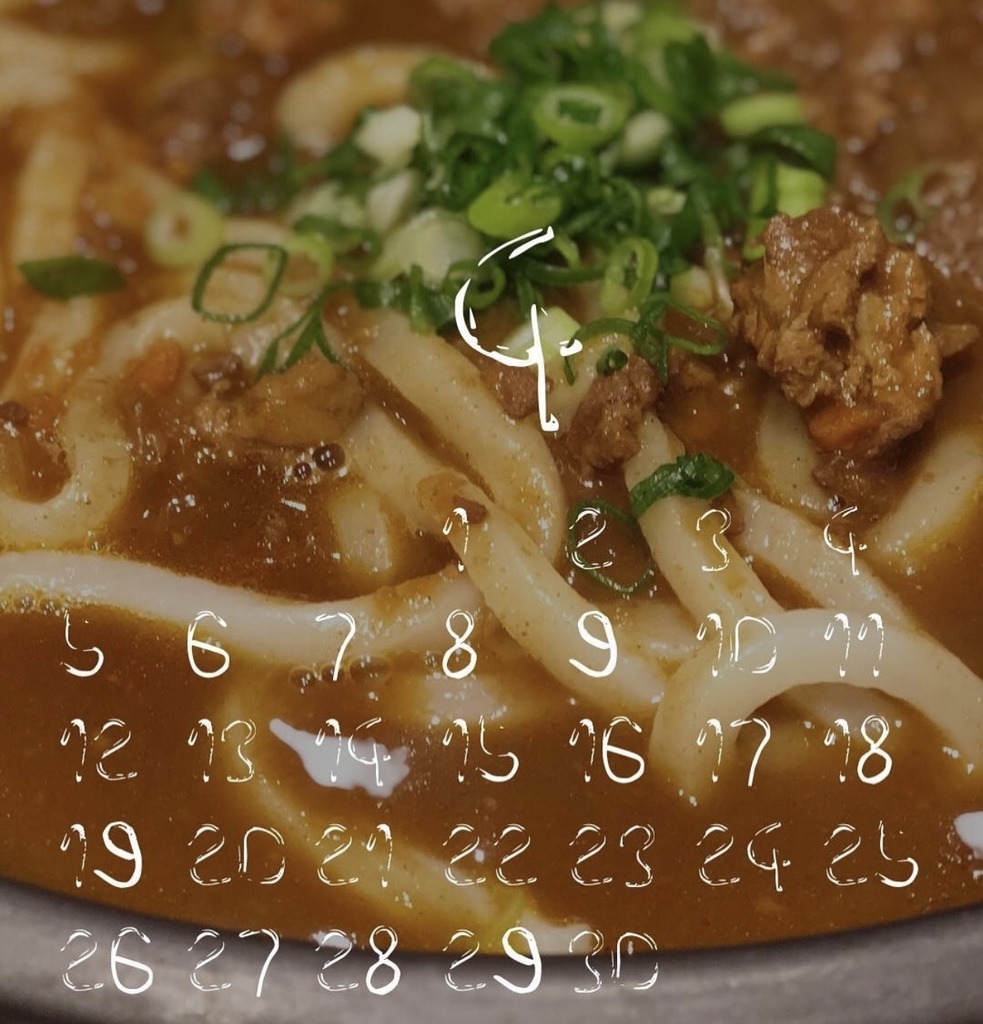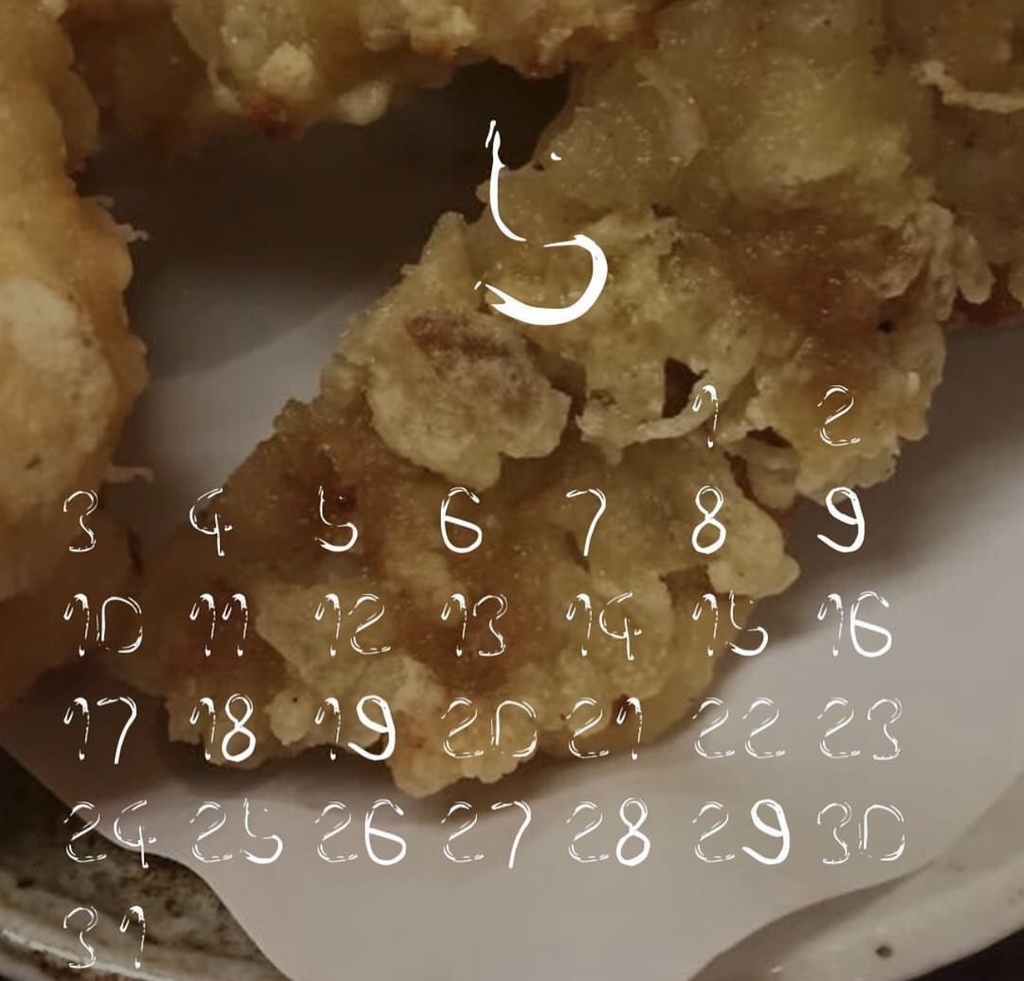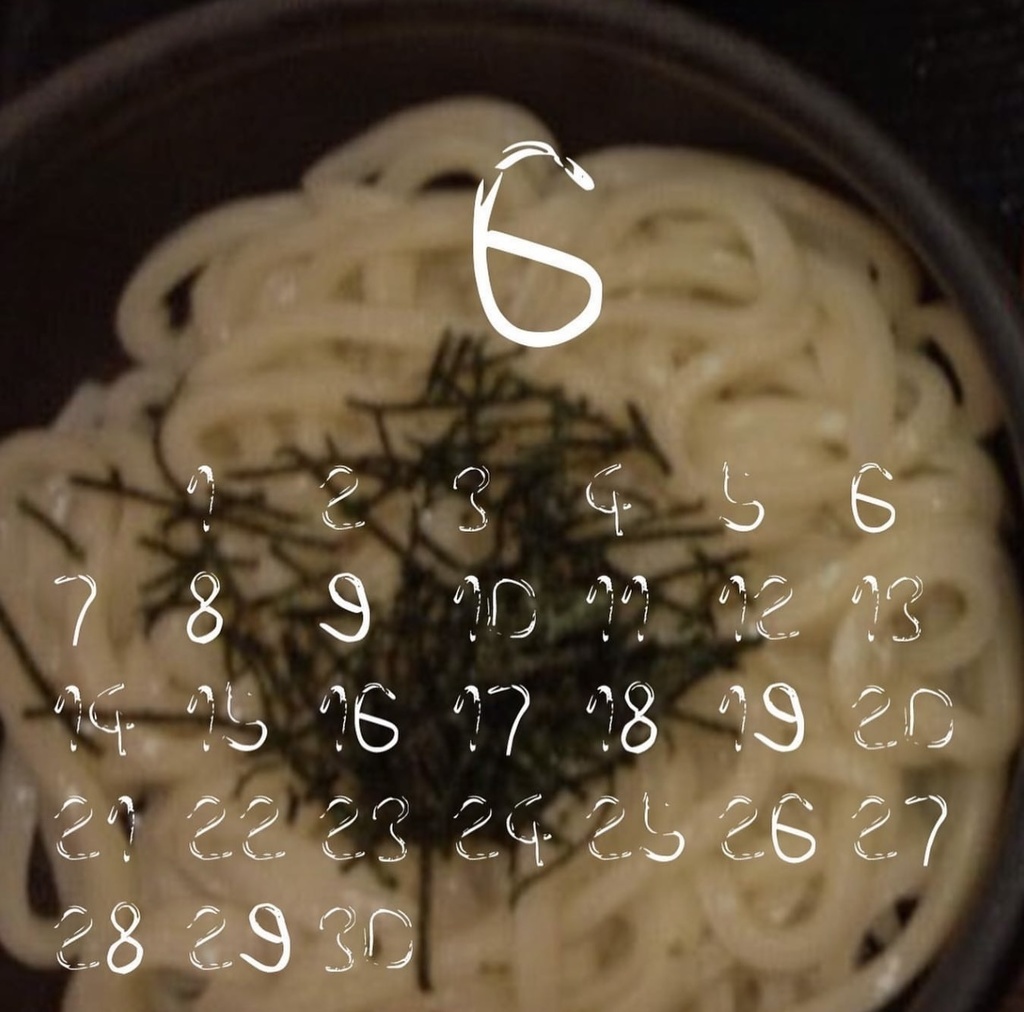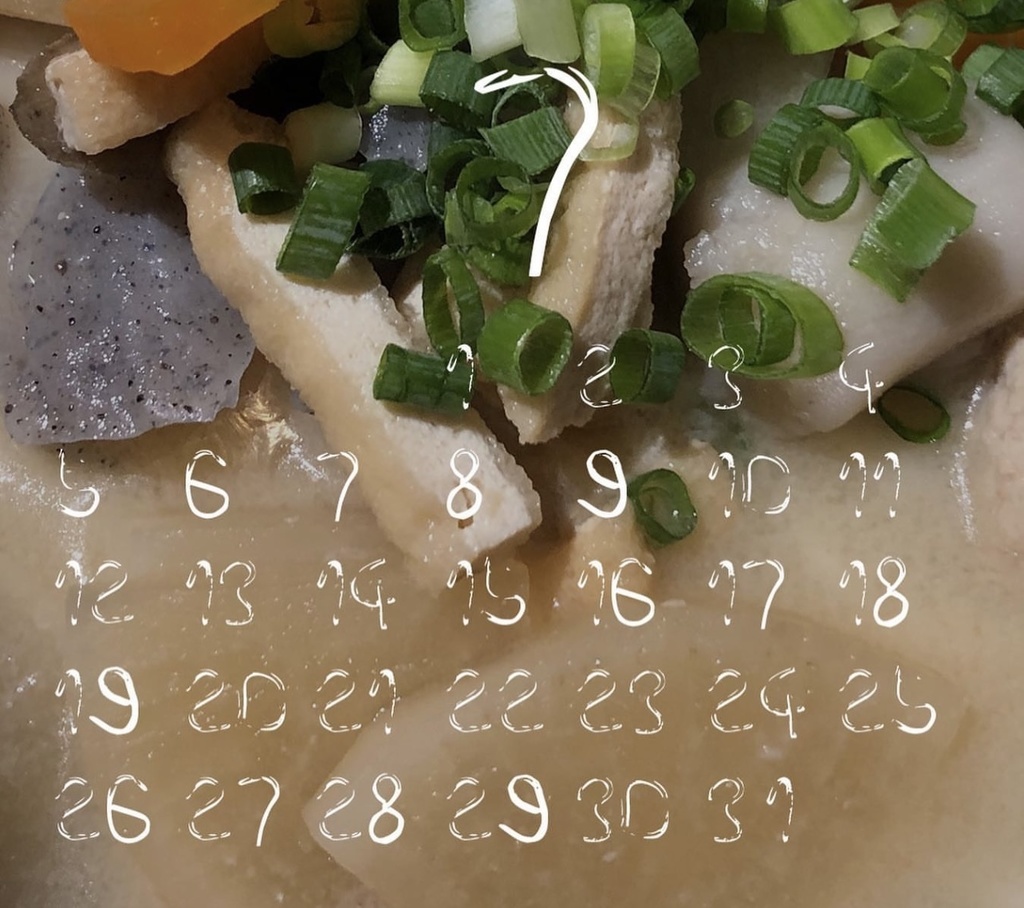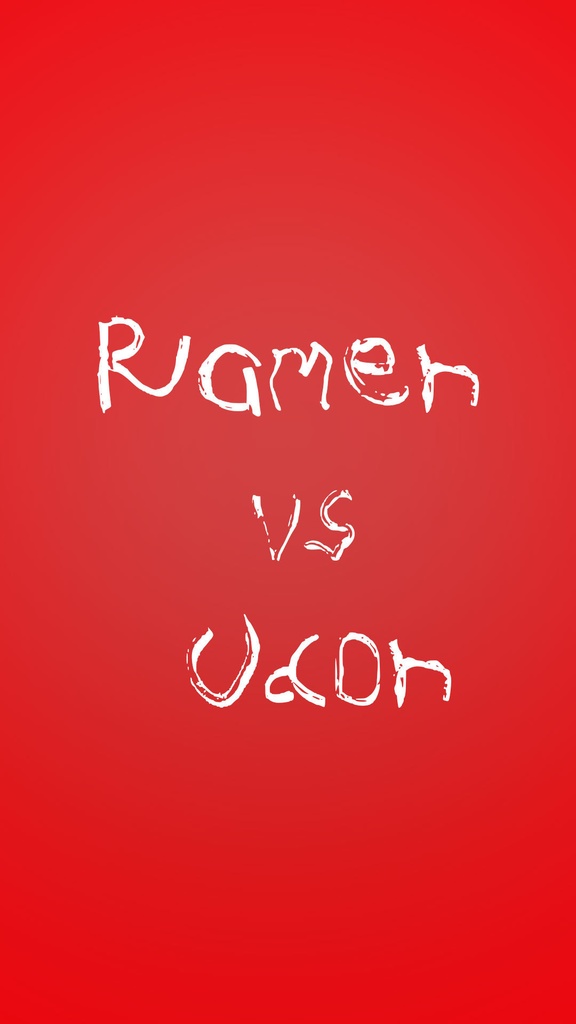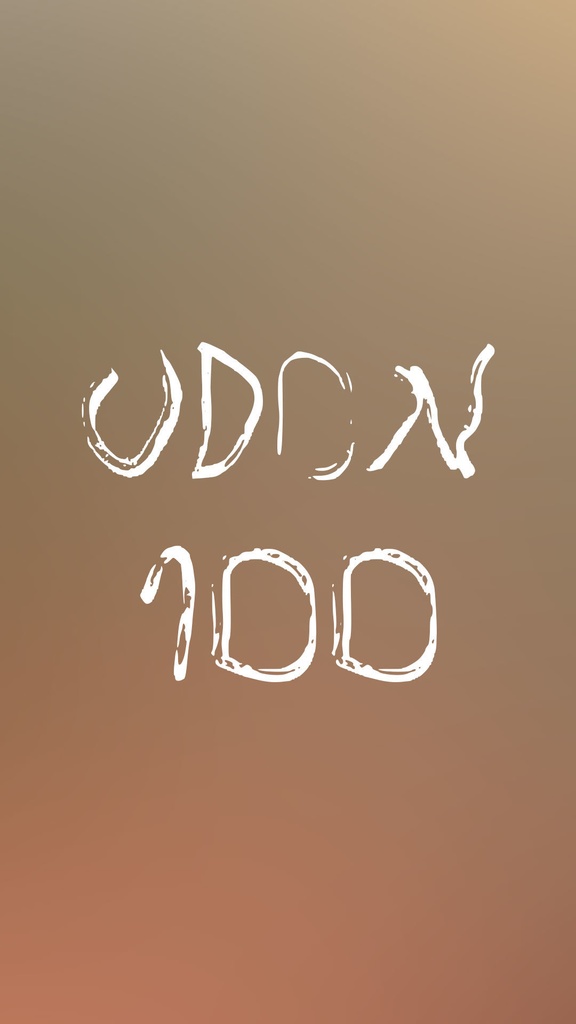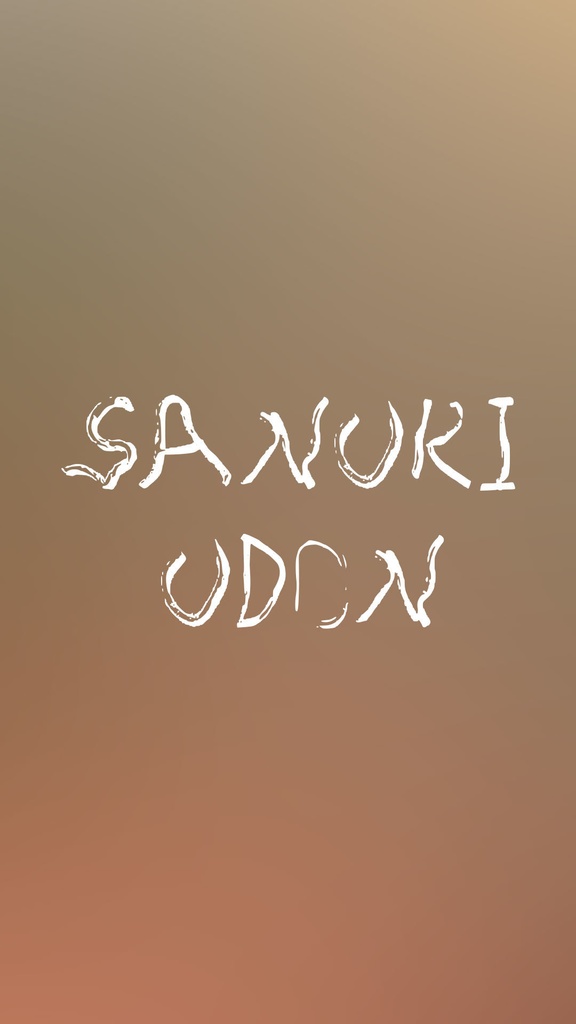
【フリー】うどんフォント
うどんフォントについて ■本フォントは、作成者がうどん好きすぎるあまり、うどんで文字を作りフォント化したうどんフォントです。 ■対応している文字は、現在数字と英語のみです。 ■企業案件は、作成者のインスタグラムからお問い合わせをお願いいたします。 https://www.instagram.com/udonfont/